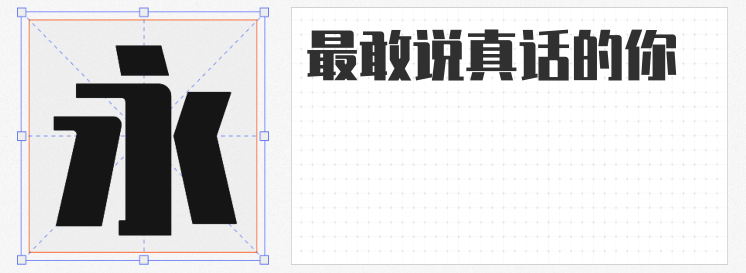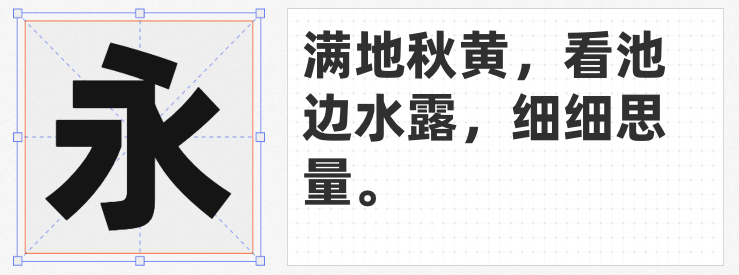
在商业设计场景中,选择一款兼具视觉冲击力与合法商用属性的超粗黑体至关重要。以下四款免费开源字体以粗重字重、现代设计语言和全场景适用性脱颖而出,成为设计师高效创作的理想选择。
作为Adobe与谷歌联合开发的开源字体,思源黑体SC Heavy采用等宽设计,笔画比例均匀,在平板电脑、智能手机等小屏设备上仍能保持清晰可读性。其SC(简体中文)版本严格遵循内地字形规范,适合国内商业项目使用。
锐字潮牌推出的这款超粗黑体以“遒劲有力、端正凝练”为核心设计理念。笔画转折处采用直角与圆角的错落搭配,既保留黑体的稳重感,又通过弧度处理增添灵动气质。在电商标题设计中,其浑厚笔触能瞬间抓住用户注意力。
阿里巴巴普惠体3.0 115 Black字重专为全场景商业设计打造。其瘦长造型与提高的重心设计,赋予字体“20岁少年”般的精气神。在标题设计中,省略出脚的笔画简化处理,既保持黑体的识别度,又通过负空间优化提升阅读效率。该字体覆盖多种语言,支持从品牌LOGO到产品包装的多维度应用,尤其适合需要国际化布局的商业项目。
基于更纱黑体、思源黑体等开源项目二次开发的句读黑体Hans Heavy,以支持中文、阿拉伯文、日文等47种语言文字为特色。其超粗字重通过加粗笔画与优化字腔比例,确保小字号下的可读性。在多语言海报设计中,该字体能统一处理不同文字系统的排版需求。